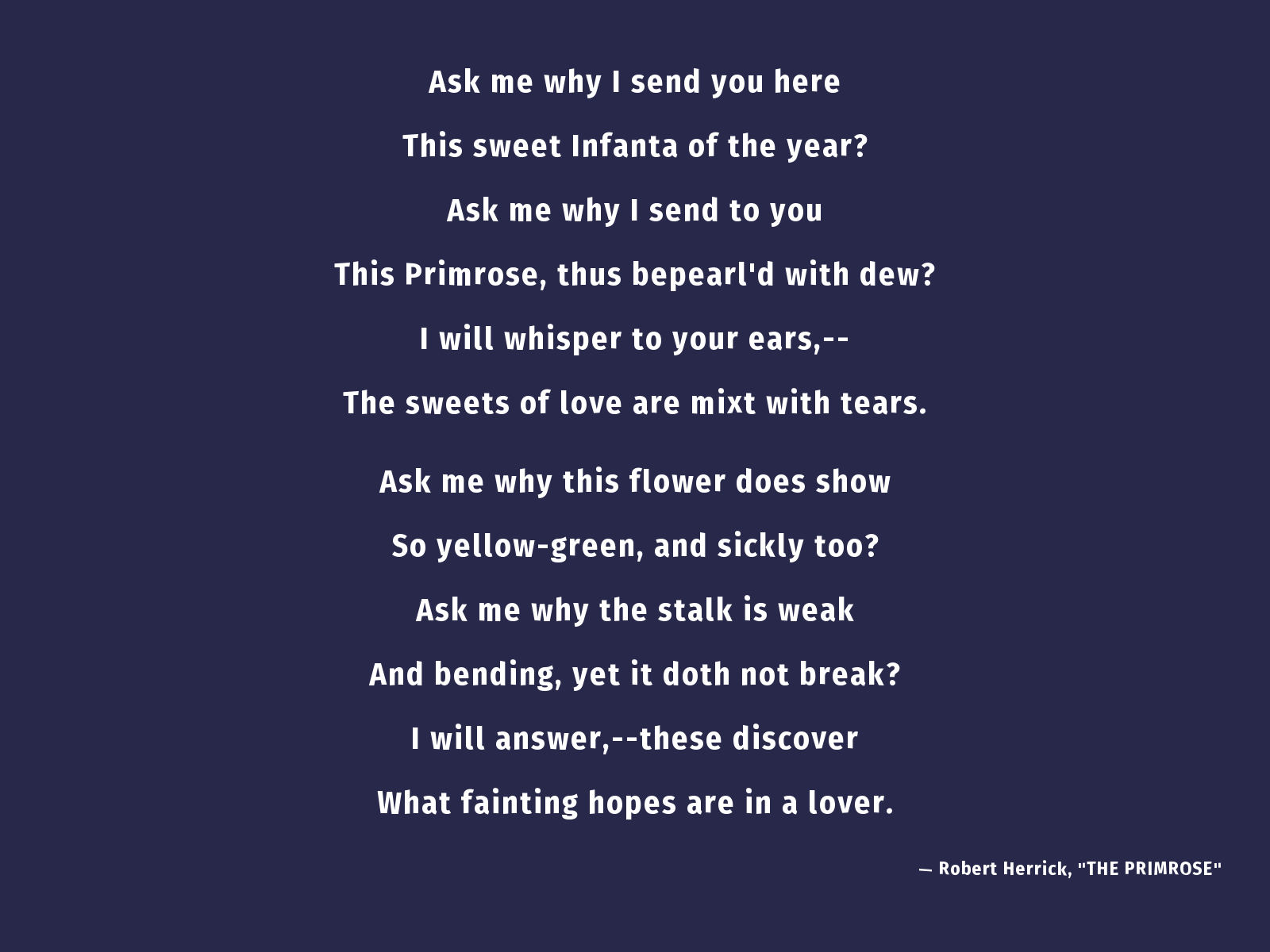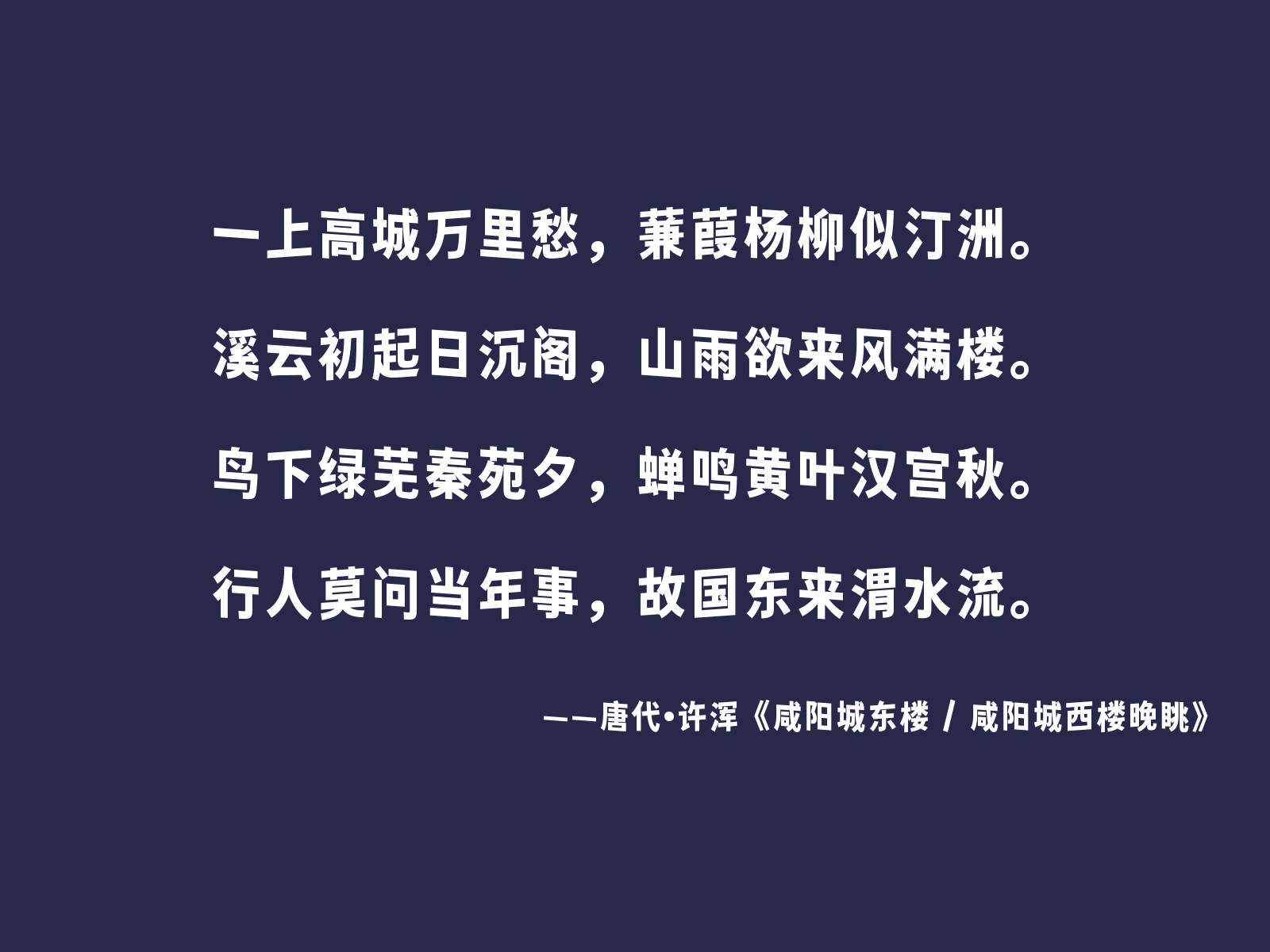
香萃自在舒畅黑是一款基于开源字体“未来荧黑”,通过简单改造而形成的中文字体,支持简繁汉字。字体呈长方形,多文本排列或长段正文使用时,会形成独特的波浪效果,极富趣味与动感、清新明快,适用于运动生活、等多种场景,可用于网络视听或各类日常商品的包装设计,允许个人或企业免费商用。未来荧黑是由思源黑体改造而成,但更具简明、轻快的特征。未来荧黑剔除了思源黑体原有的喇叭口,和口字部件的竖脚,改变了重心,使其更富有现代化。
汉字作为方块字形的文字,非常适合构建波浪形,而传统楷书写法是纵向略偏长,因此汉字比西文字体更适合做这种改造。添加随机倾斜效果后的字体,宛如竖立的纸牌,具有立体感;而长段排版时,容易做出层次感。于是这款字体应运而生。事实上,采用折笔更多、曲线更少、字面更大的字体,进行波浪化处理,能呈现更好的效果。但开源字体中,只有思源系列较适合做这类改造。由于现代汉语横向排版,所以没有选择横向随机倾斜,而是选择纵向倾斜,这同时也符合传统楷书的书写习惯,即“横画斜、竖画不斜”。
唐代许浑《咸阳城东楼》诗文内容:一上高城万里愁,蒹葭杨柳似汀洲。溪云初起日沉阁,山雨欲来风满楼。鸟下绿芜秦苑夕,蝉鸣黄叶汉宫秋。行人莫问当年事,故国东来渭水流。
罗伯特·赫里克的诗《报春花》全文,探讨爱情的甜蜜与泪水,以及恋人的脆弱希望。